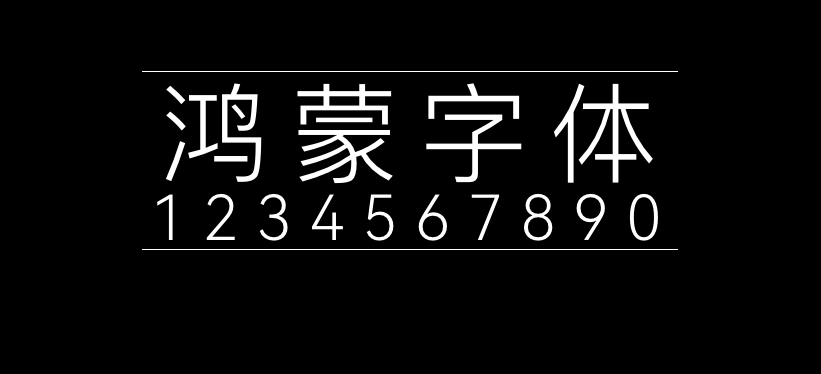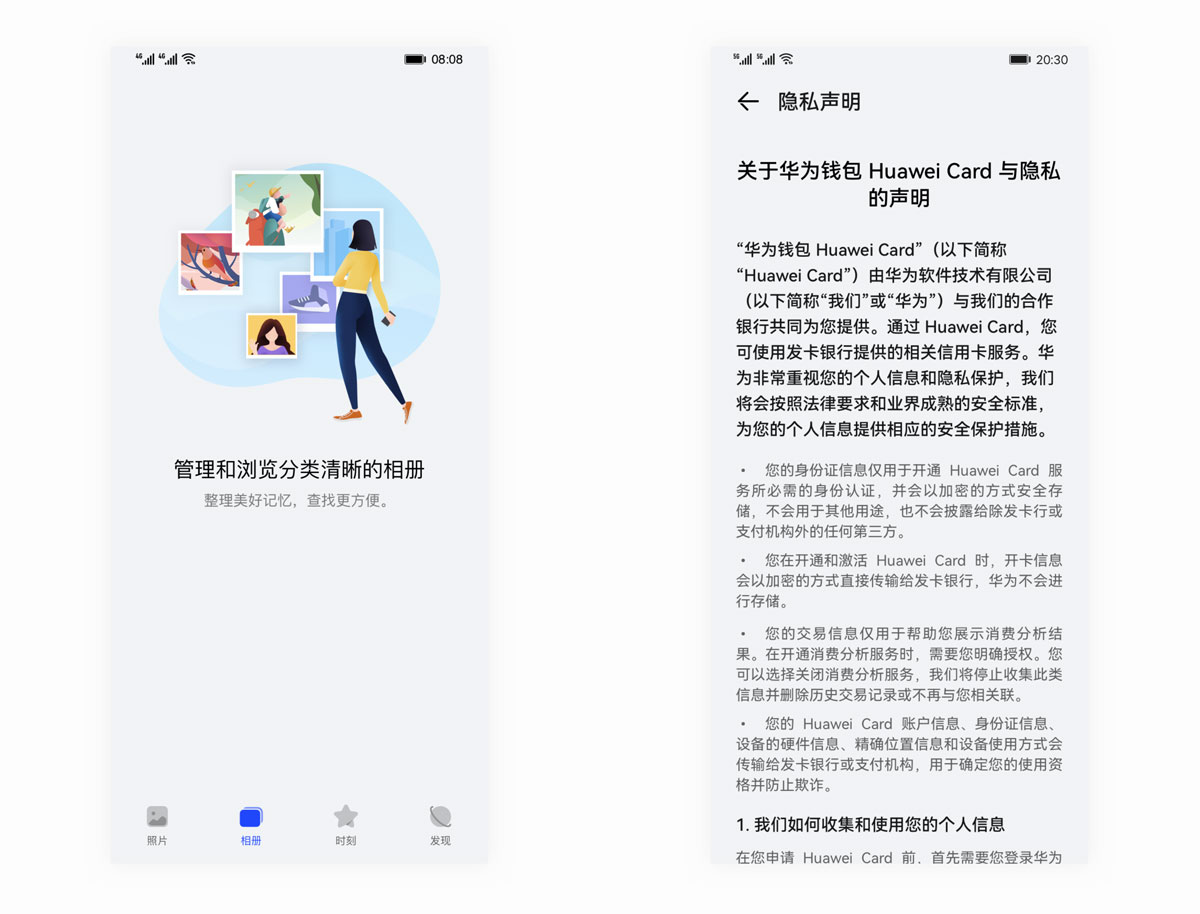
鸿蒙字体
鸿蒙字体(HarmonyOS Sans)是华为最新发布的鸿蒙操作系统HarmonyOS的自带字体,随系统一起开源,以HarmonyOS Sans Fonts License Agreement协议授权发布,您可以免费用于个人及商业用途。自由字体提供的下载包中,已包含了授权协议文件。
虽然本站将该鸿蒙字体分类为简体,事实上,鸿蒙字体对中文简体、中文繁体、阿拉伯语等语言进行了广泛支持,并支持加高、斜体等样式及6个字重,是一款不可多得的广泛支持语言的字体。
全新 HarmonyOS 字体
通过研究用户在不同场景下对多终端设备的阅读反馈,综合考量不同设备的尺寸、使用场景等因素,同时也考虑用户使用设备时因视距、视角的差异带来的字体大小和字重的不同诉求,我们为 HarmonyOS 设计了全新系统默认的字体——HarmonyOS Sans。
全新字体笔画设计
在保障字体体验的功能性前提下,我们在人文和现代中找到新的平衡。在短笔画时保持横平竖直,简约无装饰,撇捺弯钩长笔画中融入书法的笔势美学,带来全新的视觉感受。
优化字体灰度,提升阅读体验
在不同设备的应用场景下,字体的灰度会影响在弱光环境、小字号、远距离下的识别性。因此我们优化字体的灰度,让新字体在不同场景下具有更好的识别性和阅读体验。
统一多语言字形风格
我们重新设计了中文、拉丁文、希利尔文、希腊文、阿拉伯文的字形样式,支持100+语言,让多语言下阅读体验更加一致。
HarmonyOS 字体特性
动态字重粗细调节
HarmonyOS Sans支持可变特性,让用户选择他们喜欢的字体粗细来进行文本的显示。
支持更多字重能力
HarmonyOS Sans增加了Thin、Light、Bold、Black的字重能力,开发者可以选择需要的字重来构建界面的信息层级。
等宽与变宽数字字体
HarmonyOS Sans支持变宽和等宽两种样式。文本混排中使用系统默认的变宽数字,在阅读文本段落中能让阅读体验更加连贯。而等宽时钟数字在需要强调数值以及数据需要经常变化的表格和时钟数字的场景中使用时,可以保持数字字宽的对齐,同时更具图形化的呈现可以在界面中脱颖而出。
支持时钟字体特性
HarmonyOS Sans支持时钟字体特性,冒号格式会根据时间格式自动调整位置。
默认时间格式 时钟时间格式
字体排版
多设备字号层级
选择合适的字号有助于定义内容的信息层级,以及达到内容的可读性。通过研究全场景设备的显示环境、用户使用时环境的差异,我们为不同设备形态定义了一套构建信息层级的字号系统。
文本对齐规则
不同的文本对齐方式可以引导用户的视觉流向。在段落文本中文本超长换行默认使用左对齐的方式,因为人的浏览视线都是从左往右移,因此大段需要阅读的文案,采用左对齐的方式排版有利于用户快速定位,保证良好的阅读体验。相对于更常见的左对齐,居中对齐可以更容易获得用户的注意力,因此在标题上、空页面的描述文本以及在插画的引导页上使用居中对齐可以更有效地抓住用户眼球。
居中对齐可以更容易获得用户的注意力 左对齐的方式排版有利于用户快速定位